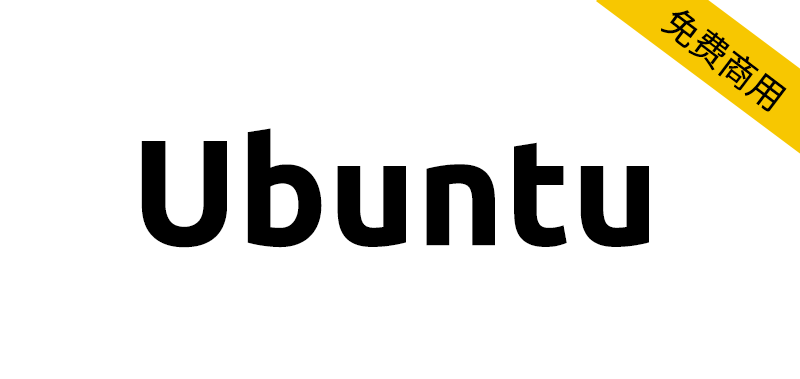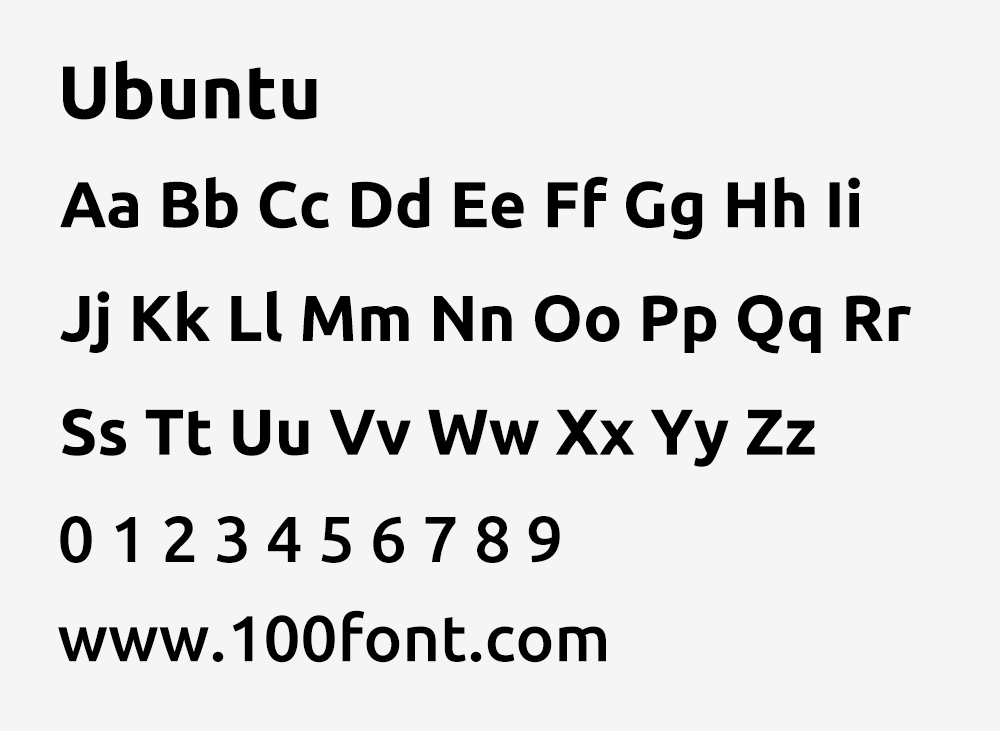
Ubuntu字体是专门为补充Ubuntu的语调而创建的。它具有现代风格,包含Ubuntu品牌特有的特点,传达了精确、可靠和自由的态度。
关于Ubuntu字体家族:Ubuntu字体家族是一组匹配的新libre/open字体。该开发由Canonical代表更广泛的自由软件社区和Ubuntu项目提供资金。字体技术设计工作和实施由Dalton Maag负责。
最终的字体Truetype/OpenType文件和用于生产字体系列的设计文件都是在开放许可证下分发的,我们明确鼓励您进行实验、修改、共享和改进。字体为无衬线字体,使用OpenType功能,并在桌面和移动计算屏幕上手动提示以保持清晰。
Ubuntu字体家族的范围包括世界各地Ubuntu用户使用的所有语言,这符合Ubuntu的理念,即每个用户都应该能够以自己选择的语言使用软件。因此,Ubuntu字体家族项目将扩展到更多的书面语言。
事实和数字:Ubuntu字体家族是一个有22种风格的无衬线字体家族,加上一个重量和宽度轴可调的可变字体。它的固定宽度配套产品UbuntuMono有8种风格和可变字体,重量轴可调。
The Ubuntu typeface has been specially created to complement the Ubuntu tone of voice. It has a contemporary style and contains characteristics unique to the Ubuntu brand that convey a precise, reliable and free attitude.
About the Ubuntu font family
The Ubuntu font family are a set of matching new libre/open fonts. The development is being funded by Canonical on behalf the wider Free Software community and the Ubuntu project. The technical font design work and implementation is being undertaken by Dalton Maag.
Both the final font Truetype/OpenType files and the design files used to produce the font family are distributed under an open licence and you are expressly encouraged to experiment, modify, share and improve. The typeface is sans-serif, uses OpenType features and is manually hinted for clarity on desktop and mobile computing screens.
The scope of the Ubuntu Font Family includes all the languages used by the various Ubuntu users around the world in tune with Ubuntu's philosophy which states that every user should be able to use their software in the language of their choice. So the Ubuntu Font Family project will be extended to cover many more written languages.
Facts and figures
The Ubuntu font family is a sans-serif typeface family available in 22 styles plus a variable font with adjustable weight and width axes. . Its fixed-width companion, Ubuntu Mono, comes in 8 styles and a variable font with an adjustable weight axis.